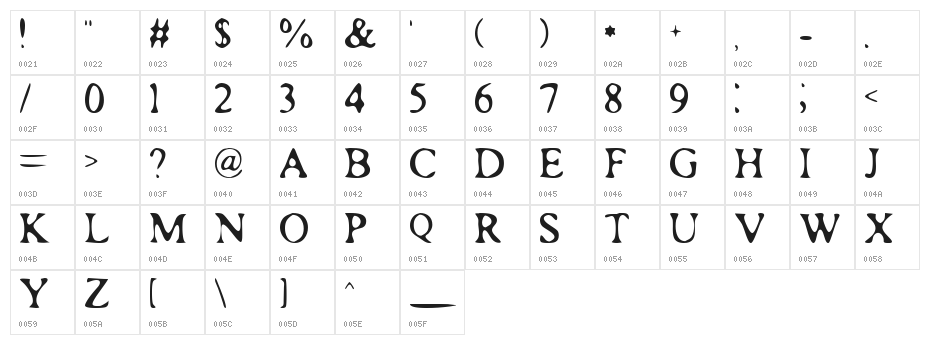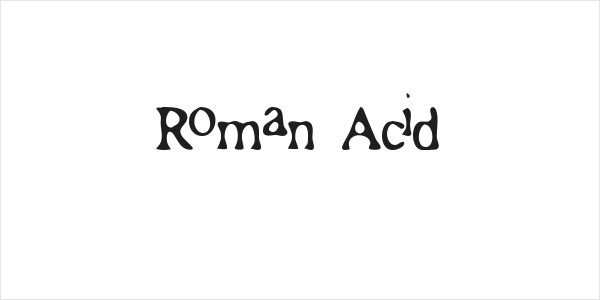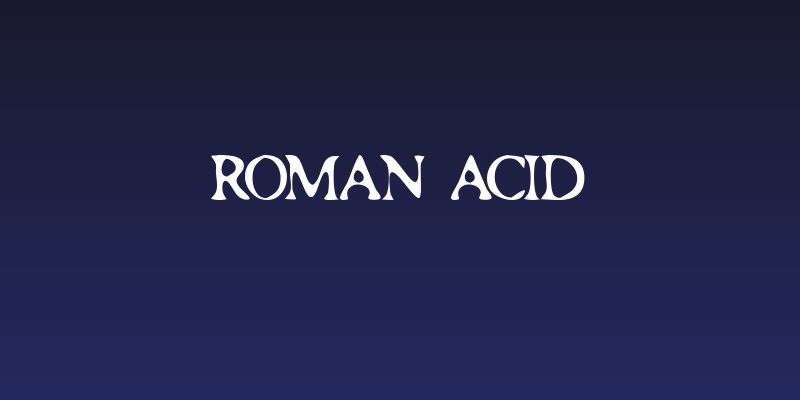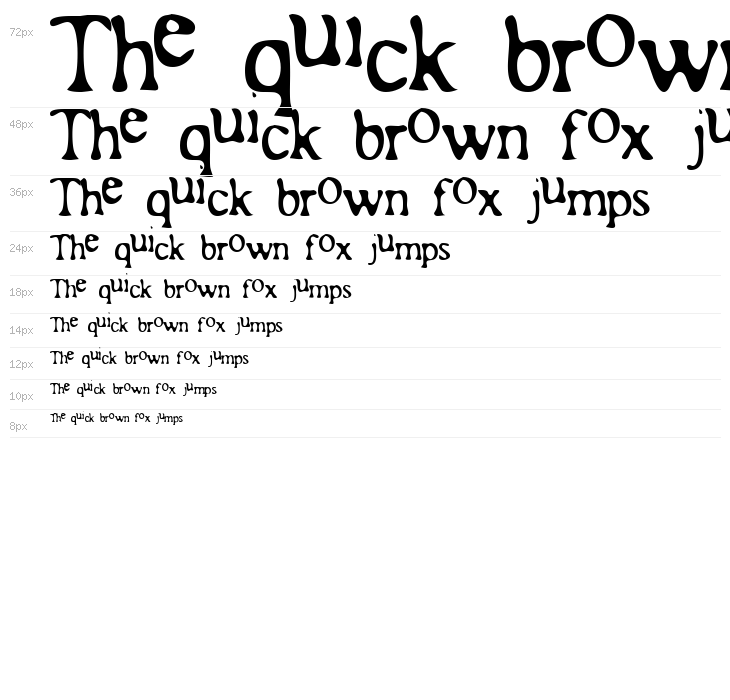
Roman Acid Font
| संस्करणः | Version v1.0 - Variation on Times New Roman |
| समग्र शैली | Modern, Retro, Eccentric |
| उपयोग का मामला | Headlines, Logos, Artistic Projects |
| सुझाए गए प्रोजेक्ट | Ideal for posters, album covers, children's books, and creative branding. |